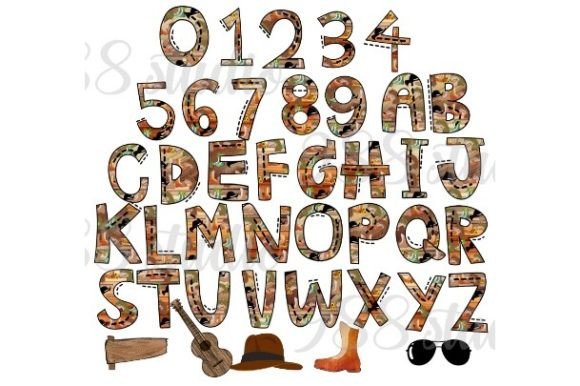
Doodle Country Fonts Png Cowboy Western
หากคุณกำลังมองหาเนื้อหาคุณภาพสูงเช่น Doodle Country Fonts Png Cowboy Western แพ็คเกจพรีเมียมนี้เป็นตัวเลือกที่ยอดเยี่ยมสำหรับโปรเจ็กต์สร้างสรรค์ของคุณ